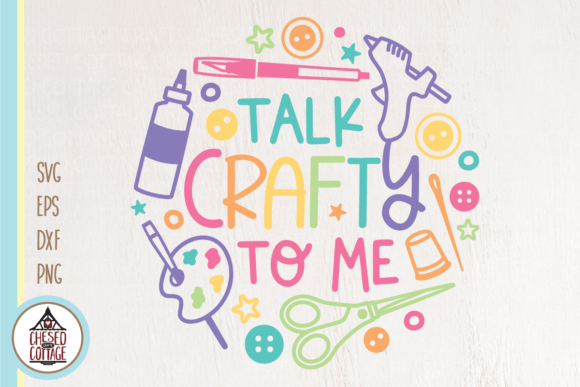
Talk Crafty to Me
Hassasiyetle hazırlanan Talk Crafty to Me, temiz vektörler, pürüzsüz tipografi ve içinizin rahat etmesi için ticari bir lisans sağlar.